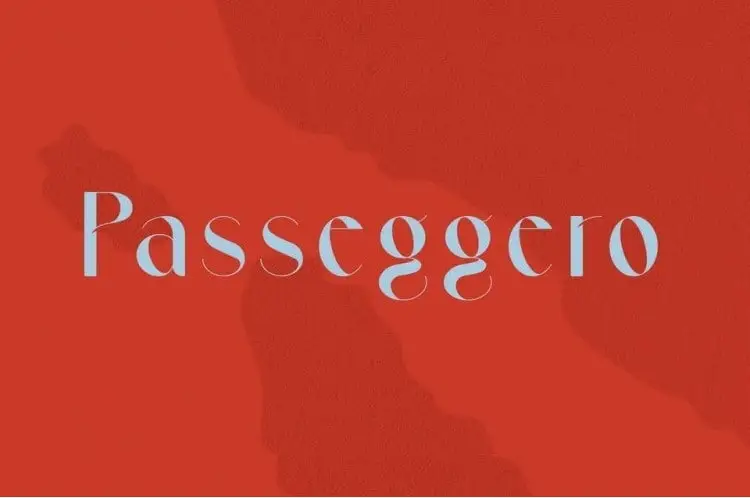
Passeggero Sans Serif Font – Download Grátis
A fonte ‘Passeggero Sans Serif’ é uma opção perfeita para quem está buscando uma fonte amigável e clean para ambientes festivos como postais de natal ou convites de eventos. Inspirada na elegância do filme Professione Reporter, de Michelangelo Antonioni, e no desânimo das suas cenas, a ‘Passeggero Sans Serif’ é um font display que se destaca por sua modernidade e nostalgia. Este estilo dinâmico e nostálgico é ideal para logotipos, headlines ou qualquer texto curto a médio comprimento, onde uma estética marcante e distintiva seja necessária. Adaptável a diversos ambientes de uso, o ‘Passeggero Sans Serif’ é uma escolha inteligente para designers que buscam expressar sua personalidade visual de maneira única e inconfundível.